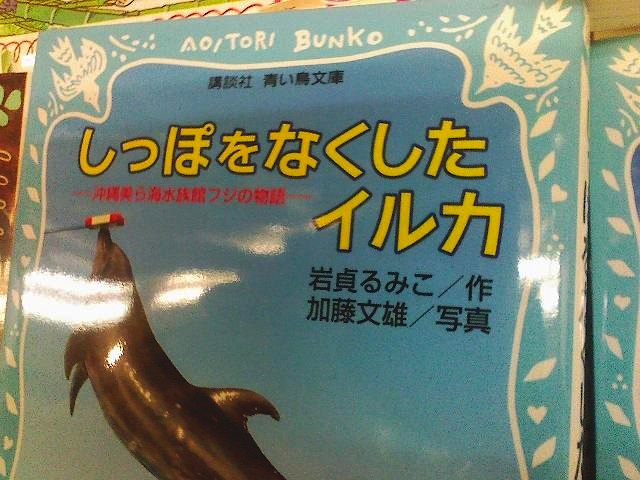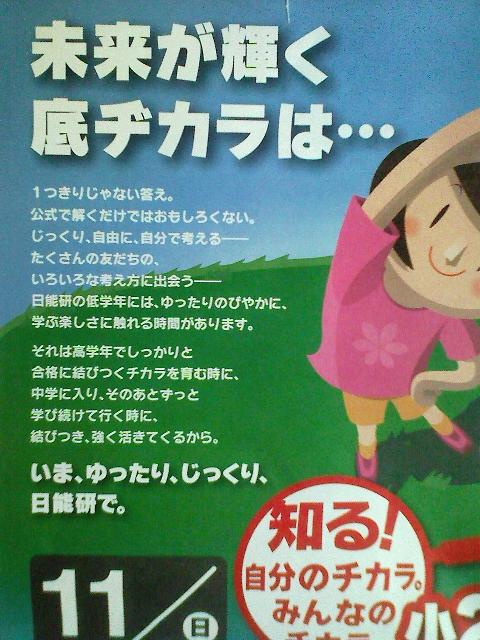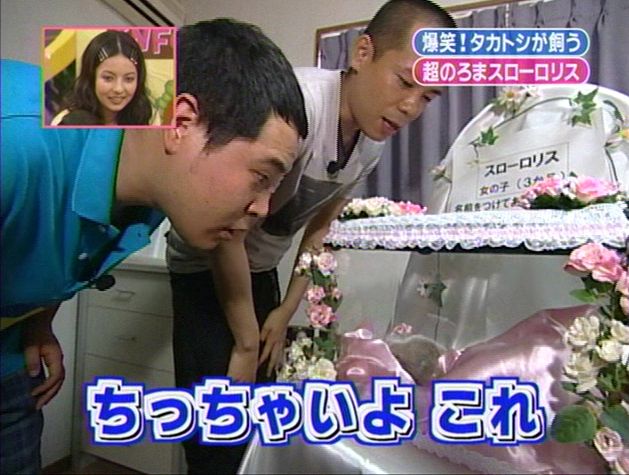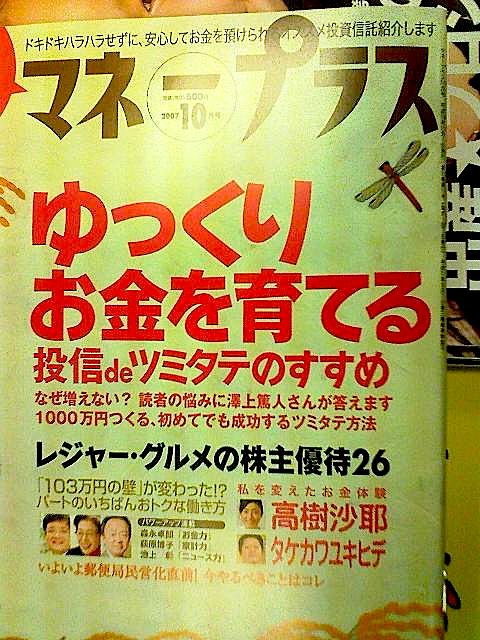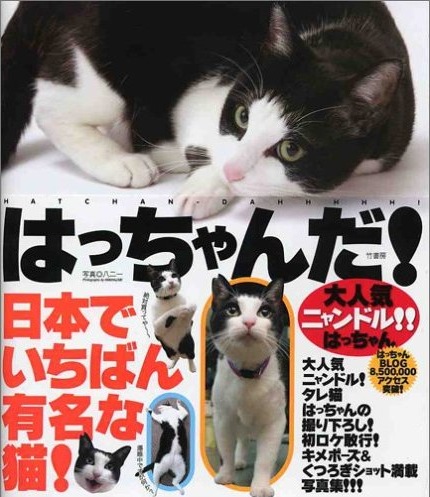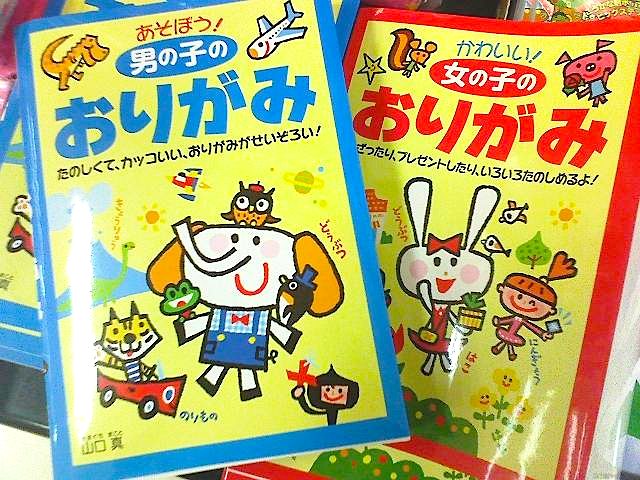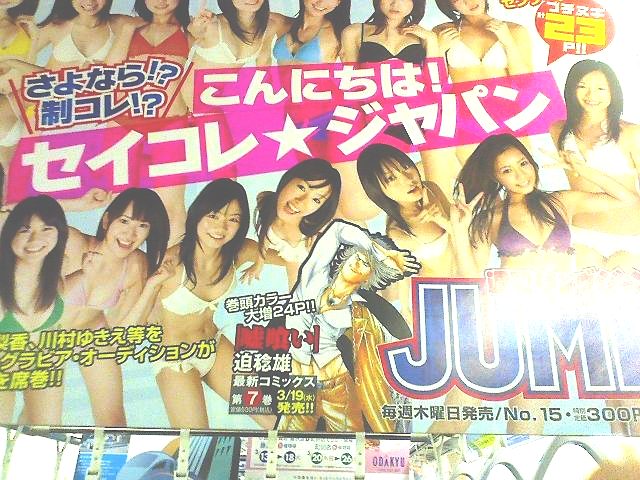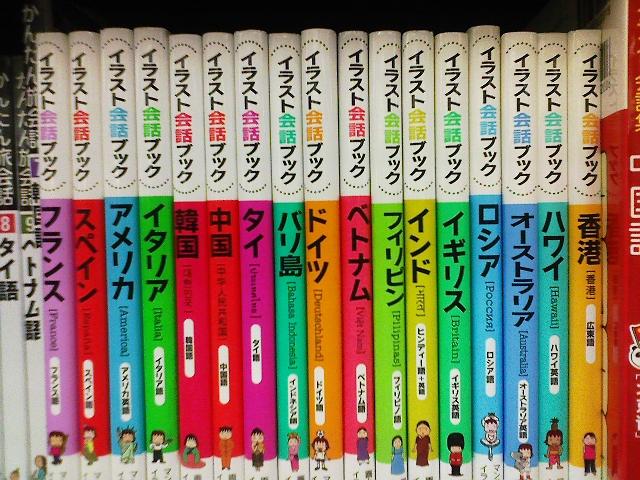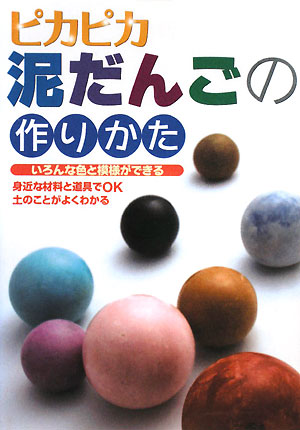
本の表紙 さとうゆたか
書名:親が知らないケータイ・ネットの世界
著者:大川内麻里
発行:実業之日本社
子供向けの料理本 さとうゆたか
購読している新聞のオマケの子供向け料理本。
本文中の見出しにも、細いわんぱく書体がたくさん使われていた。
大学のポスター さとうゆたか
住む地域が変わると、目にするポスターも変化する。
見開きの新聞広告 さとうゆたか
きょうの朝刊、カラー2ページ分の広告
木村屋のパン さとうゆたか
夏だけの限定商品でしょうか。
怪しい… さとうゆたか
発行:鉄人社
こういう本も読んだりします…。
本の表紙 さとうゆたか
書名:たたかうお嫁さま
著者:けらえいこ
発行:メディアファクトリー
「お」の文字の点が、●に変更されています。
近所の公園で開催 さとうゆたか
つづき Mighty
キャピーとわんぱくです。
投げ込みチラシ Mighty
こんなのがありました。